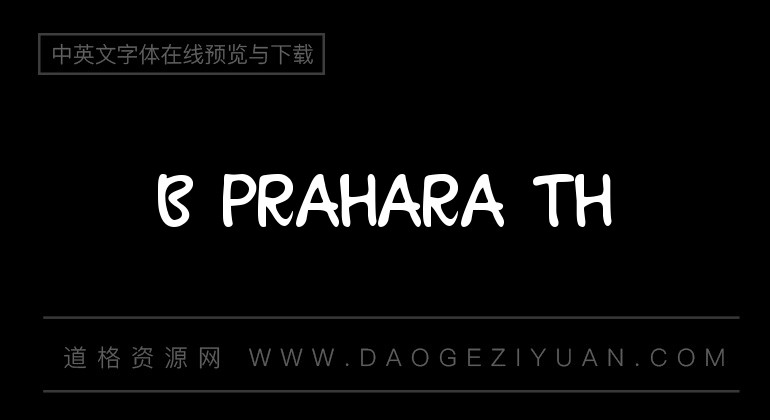
B Prahara TH
B Prahara TH 是一种华丽的印度尼西亚语字体,适用于多种设计应用,如海报、标志、标题、印刷品、包装等。它具有优美的笔画和复杂的设计,展现了印尼文化独特的美感。 B Prahara TH 字体包含拉丁字母、西里尔字母和印度尼西亚语字符,覆盖多种语言。它可用于多种项目,包括书籍、广告、品牌设计和网页设计等。 该字体的设计师是Agung Syaifudin,他在创作B Prahara TH 时受到印尼传统文化和艺术的启发。B Prahara TH 具有鲜明的印尼特色,是一种非常优美的字体,适合用于独特的设计项目。
B Prahara TH是一款非常不错的手写艺术字体,具有很好的视觉感,适合于文化类的宣传设计、商业类品牌的广告和产品包装设计以及个性化文字排版等较多场景。